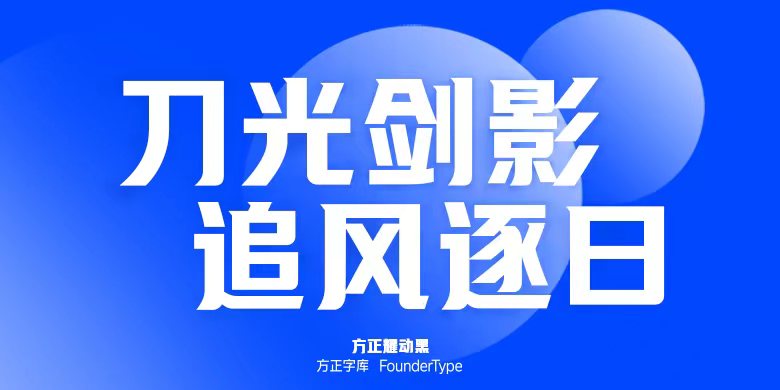
方正耀动黑
字体品牌: 方正字库设计师:曹基殿 字体分类:创意字体 字体属性:精品字 字符集:大陆简体(GB2312-80) 发布时间: 2023
耀动黑是一款创意黑体字,中宫宽博、字面略高、字重较粗,有着强烈的力量感和震撼的视觉冲击;笔形方圆结合,顶端尖角的处理在保持结构稳定的前提下丰富了字体个性。适合于影视综艺、电商、包装、品牌名称、各类商业海报、游戏、户外广告标题等。